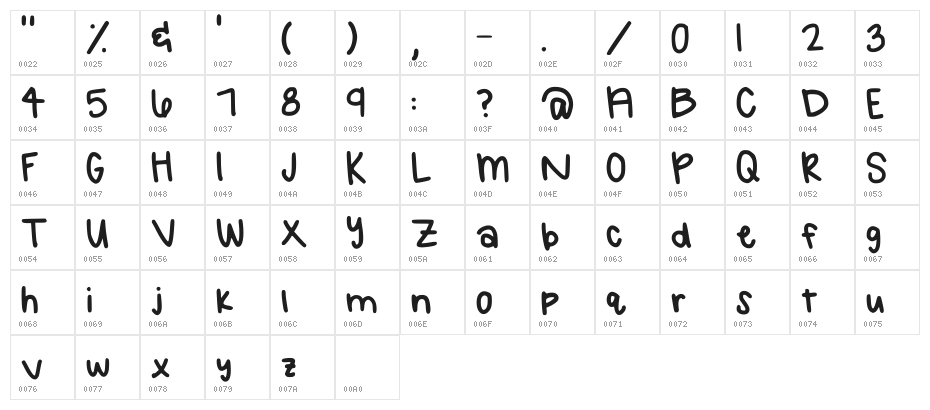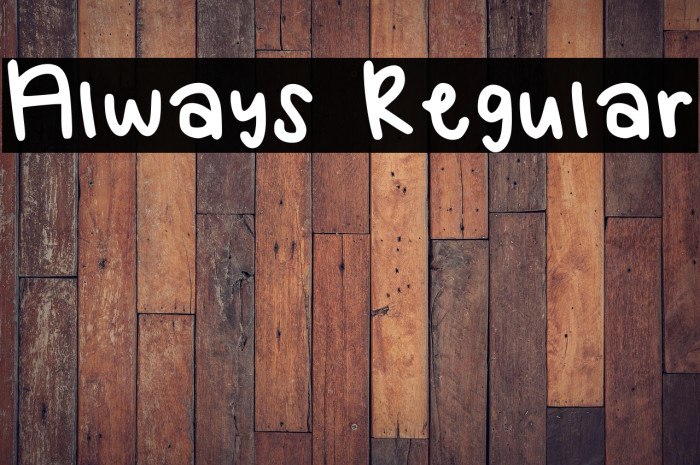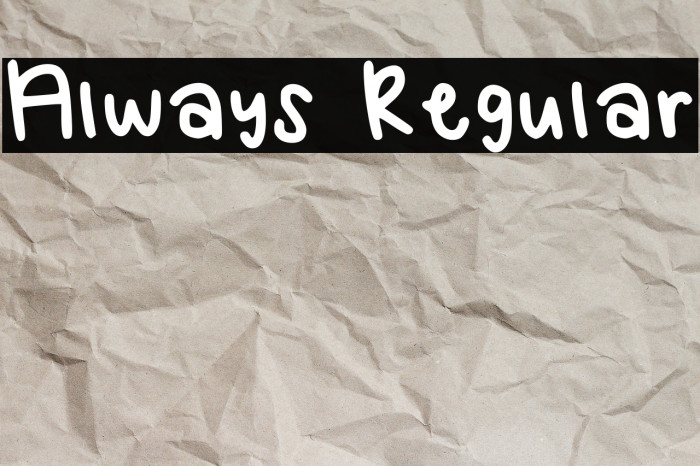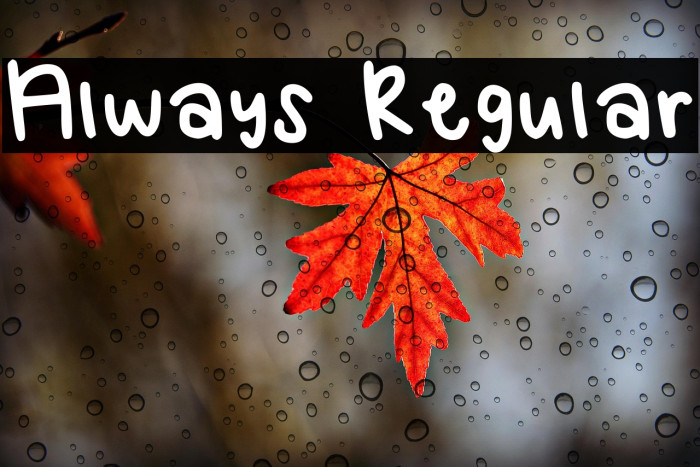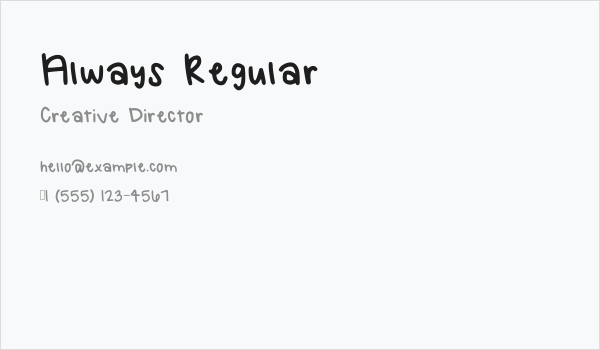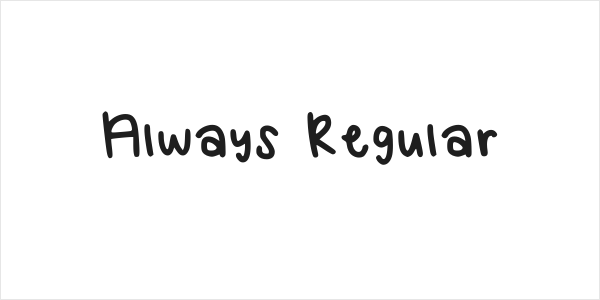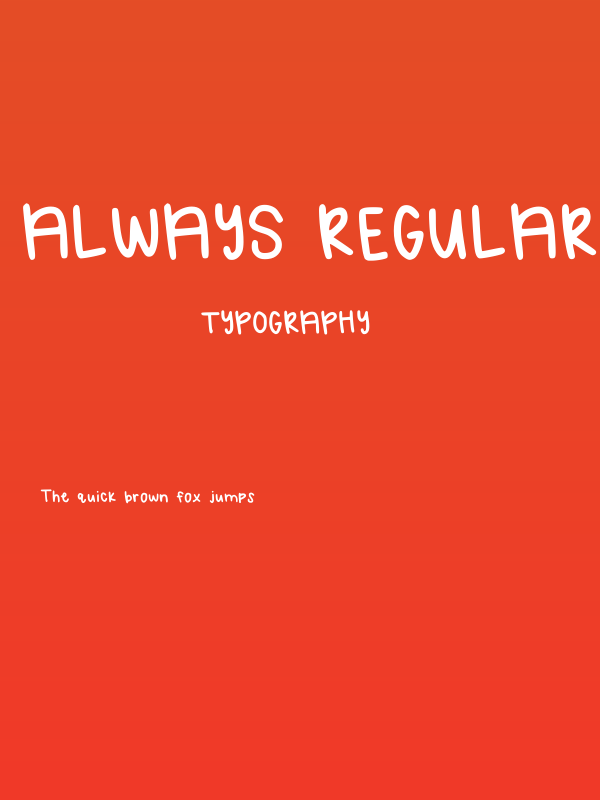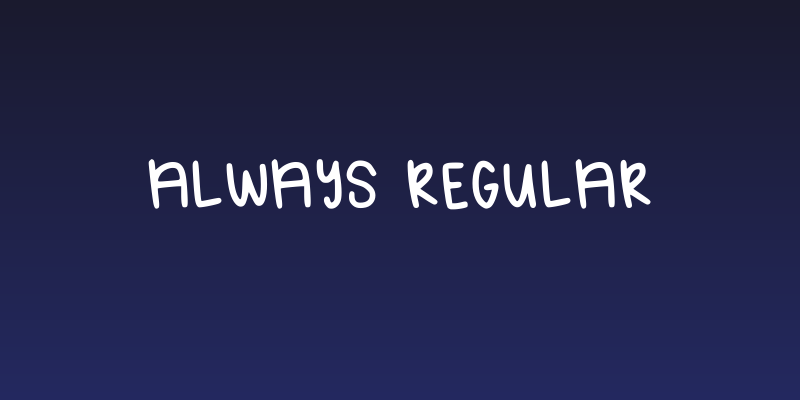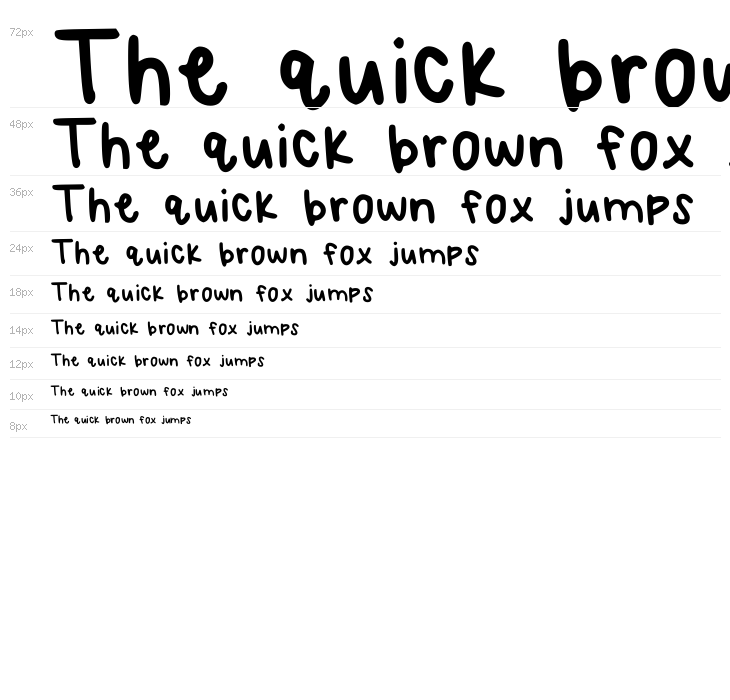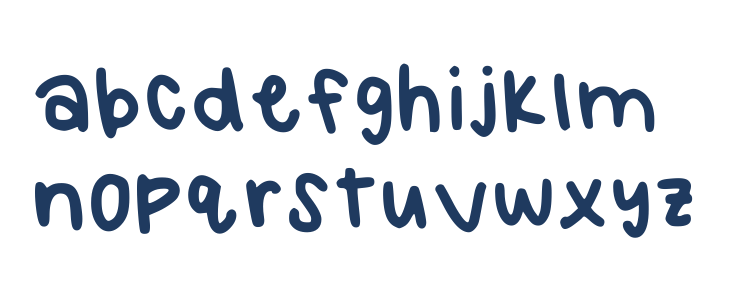
Always Regular Font
| Stile generale | Casual, Playful |
| Caso d'uso | Headlines, Logos, Creative projects |
| Progetti proposti | Ideal for invitations, greeting cards, children's books, and creative projects requiring a personal touch. |